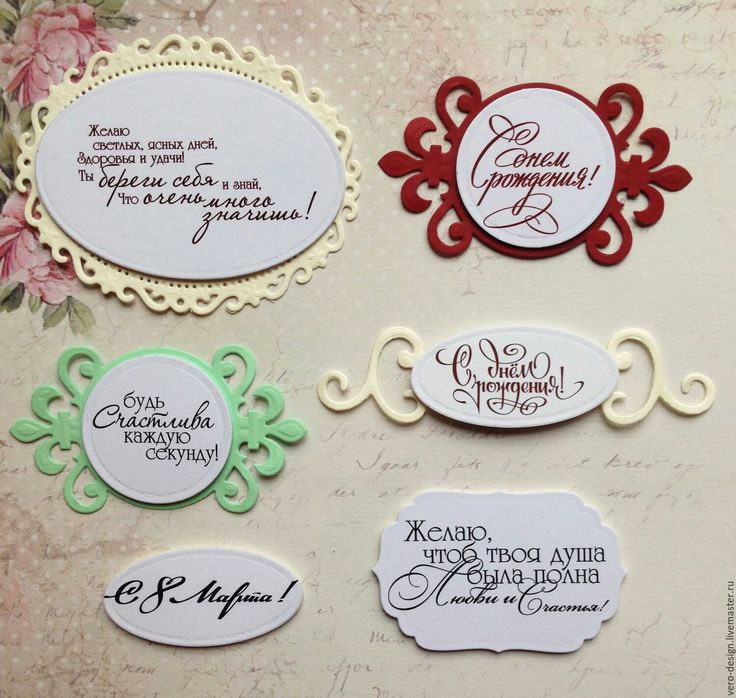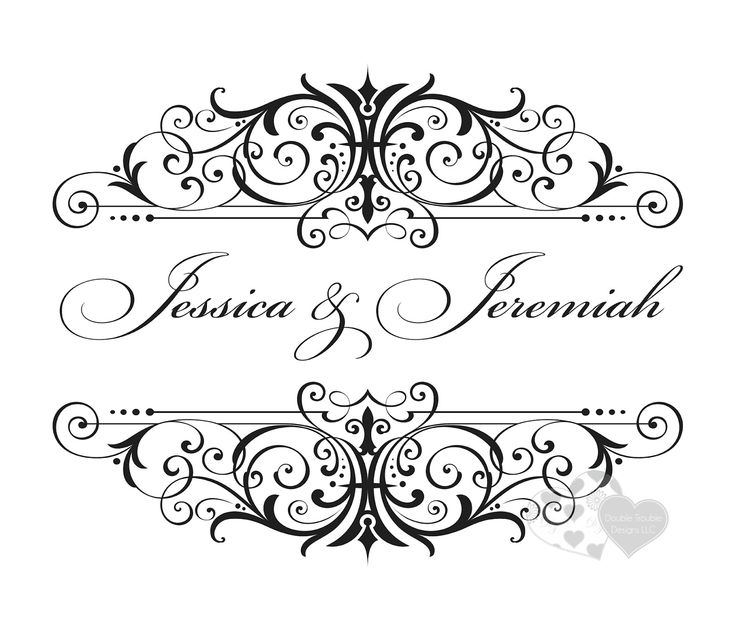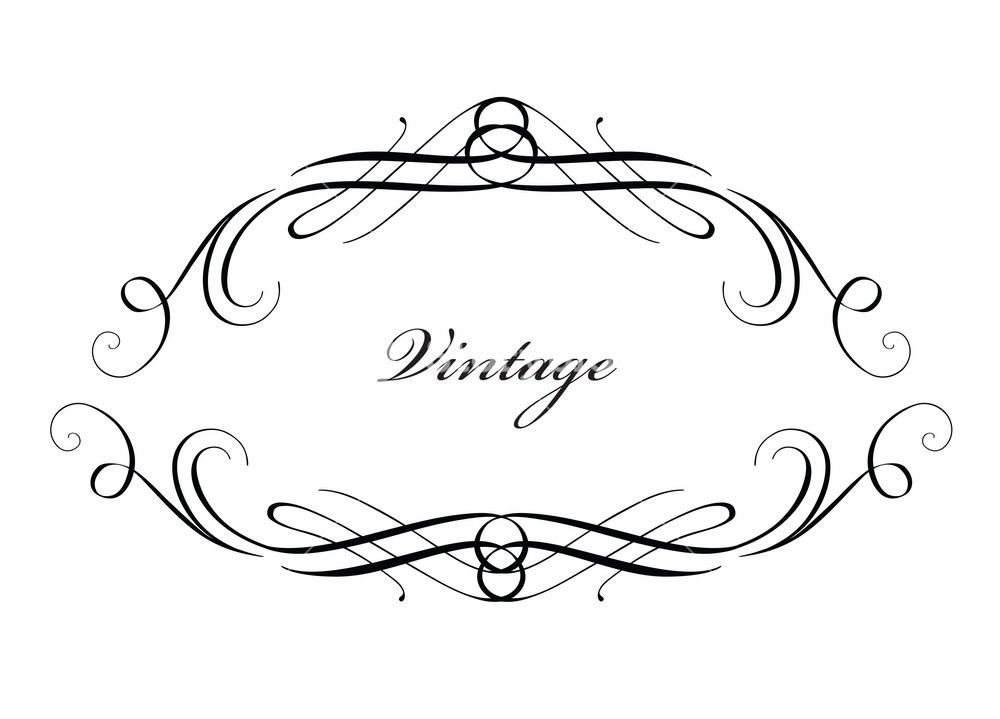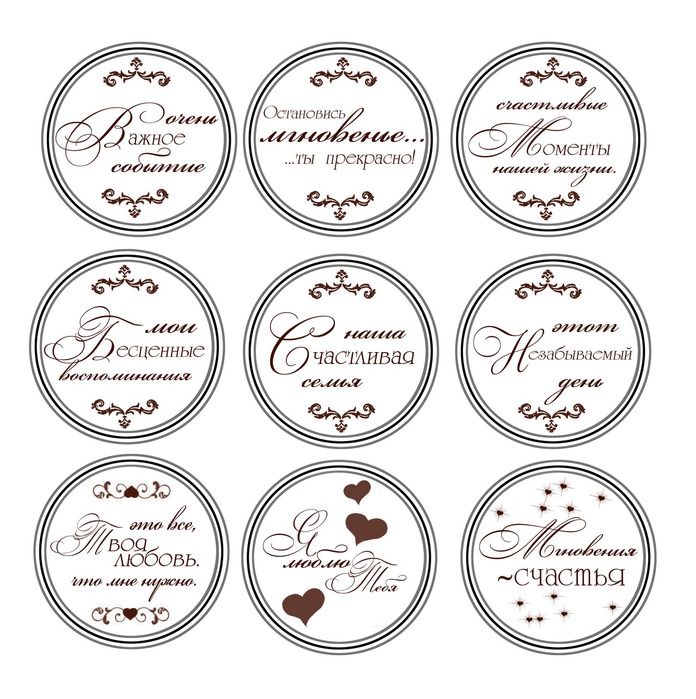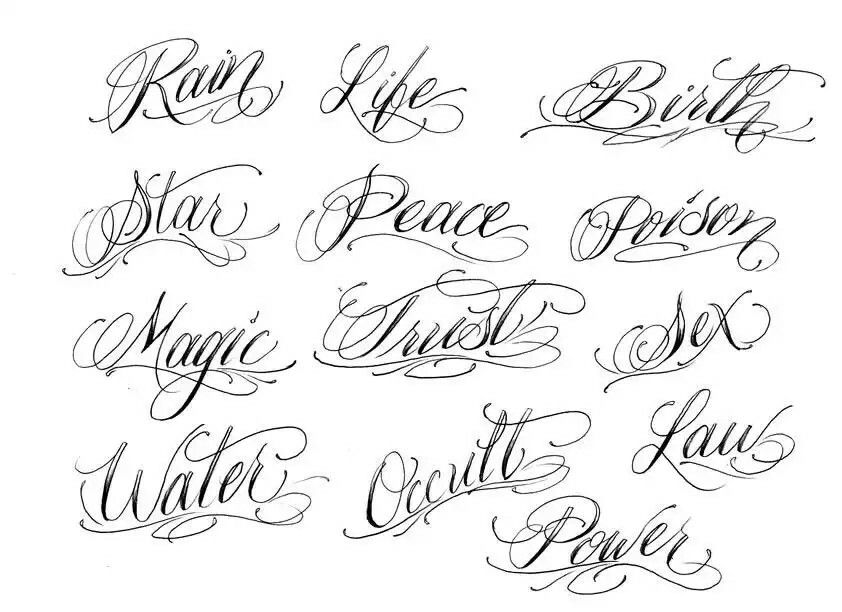
Как написать красиво текст без программ [ОБЗОР]
Часто в последнее время спрашивают, как написать красиво текст без программ, сделать надпись или подпись на картинках быстро и легко. Элементарно, берём фломастеры и прямо на мониторе рисуем…
Сейчас покажу и расскажу, как сделать красиво текст за несколько секунд без всяких программ! Это действительно легко и быстро можно сделать, если знать где и как.
Полученные сегодня знания помогут красиво оформить поздравительную открытку, сделать скачанные из интернета обои на рабочий стол оригинальными и индивидуальными… а для тех у кого есть свой сайт это вообще находка и спасение кучи времени.
Помогать нам делать красивую надпись или текст будут парочка удобных сервисов. Безусловно, подобных онлайн помощников гораздо больше существует в сети, но как всегда — советую всё самое лучшее!
Написать красиво текст: способ №1
Самым удобным, простым и быстрым способом сделать красивую надпись или подпись на своём изображении, как считаю, можно воспользовавшись услугой effectfree.
ru.
На этом замечательном сайте сможете не только красиво текст оформить, но и вообще сделать, что угодно со своими изображениями. Наложить одно на другое, применить кучу эффектов, сделать календарь, вставить фото в красивую рамку… даже этикетку на бутылку создать со своим фото можете.
Там всё на русском языке и интуитивно понятно. Но всё-таки опишу в двух словах, как написать красиво текст, раз уж тема статьи именно об этом.
Итак, переходим по ссылке указанной выше и видим…
Если надо сделать надпись на фото, то указывайте его расположение на своём компьютере или вставьте ссылку на него из сети.
А если хотите создать просто красивый текст — сделайте заранее чистое изображение и загрузите на сервис, как фото. Далее экспериментируйте методом научного тыка — вариантов море. Единственный минус, как по мне — малое количество шрифтов.
После того, как наигрались и решили, что результат устраивает — жмите кнопку «Наложить текст» …
Вот и вся сложность!
Написать красиво текст: способ №2
Вторым помощником в создании красивого текста может стать cooltext.
com. Тут возможностей поменьше, но зато шрифтов тысячи. Вдобавок можно сделать кнопочку свою на сайт или ещё куда. Переходим по ссылке и видим…
Это стили текста. Выбирайте понравившийся и кликайте по нему.
Всё на английском, но интуитивно понятно. В верхнюю рамочку вписываем свой текст, «Font» — это шрифт. Кликаем по нему, чтоб выбрать красивый и нужный.
Попали в категории шрифтов — выбирайте одну из предложенных и снова клик…
Думаете, что это все шрифты? Обратите внимание на буковки указанные мной стрелками — это названия шрифтов по первым буквам. Жмите букву и будет огромнейший выбор.
Со шрифтами разобрались. Теперь:
- «Text Size» — размер текста (ещё ниже — цвет текста)
- «File Format» — формат для сохранения
- «Background Image» — фон под текстом
- «none» — без фона
- «Text Gradient» — переход цвета из одного в другой
- «Use Shadow» — наложение тени
Удовлетворяет полученный результат — сохраняем и скачиваем свой шедевр…
Безусловно, в Фотошопе сможете создать гораздо более разнообразные эффекты, но это лишь при условии, что владеете хотя бы азами работы в этой программе.
Мне лично потребовалось несколько месяцев вникания и практики, чтоб постичь примерно 1% всех возможностей этого монстра работы с графикой.
Зачем такие жертвы, если написать красиво текст можно без программ и за считанные секунды?
Как сделать красивую надпись в сториз Инстаграм
Многие блогеры пытаются разнообразить свои сториз, вставляя необычные надписи поверх видео или фото.
Это смотрится очень креативно, детали привлекают внимание, а иногда даже заставляют подписчиков пересматривать истории с данными эффектами. Многие также хотят разнообразить свои истории, но не знают как это сделать. Есть несколько возможностей сделать красивые надписи в историях Инстаграм.
Способ 1: Первый способ — максимально простой. В последнее время появилось множество интересных масок, которые позволяют накладывать необычные надписи, написанные красивым шрифтом. Мы сделали для вас целую подборку таких милых надписей в масках, которые вы можете использовать для своих историй. Они сделаны как на русском, так и на английском языках, белым цветом, поэтому не отвлекают от основной картинки. То есть, все, что нужно сделать: найти автора подходящей маски, выбрать красивый эффект в списке масок, и нажать кнопку попробовать, записывая видео.
Способ 2: Второй способ немного сложнее, но тем не менее такие шаги сможет выполнить каждый желающий.
Многие из нас учились письму курсивом в очень раннем возрасте, так как раньше это было частью школьной программы. Курсив, или письмо, не отрывая пера от бумаги, дает вариант почерка, отличный от того, что мы хотим в каллиграфии.
Если вы посмотрите на пример рукописного шрифта, вы увидите, что буквы имеют тенденцию быть высокими и узкими, а петли выглядят более вертикальными и менее круглыми, чем в версии для каллиграфии.